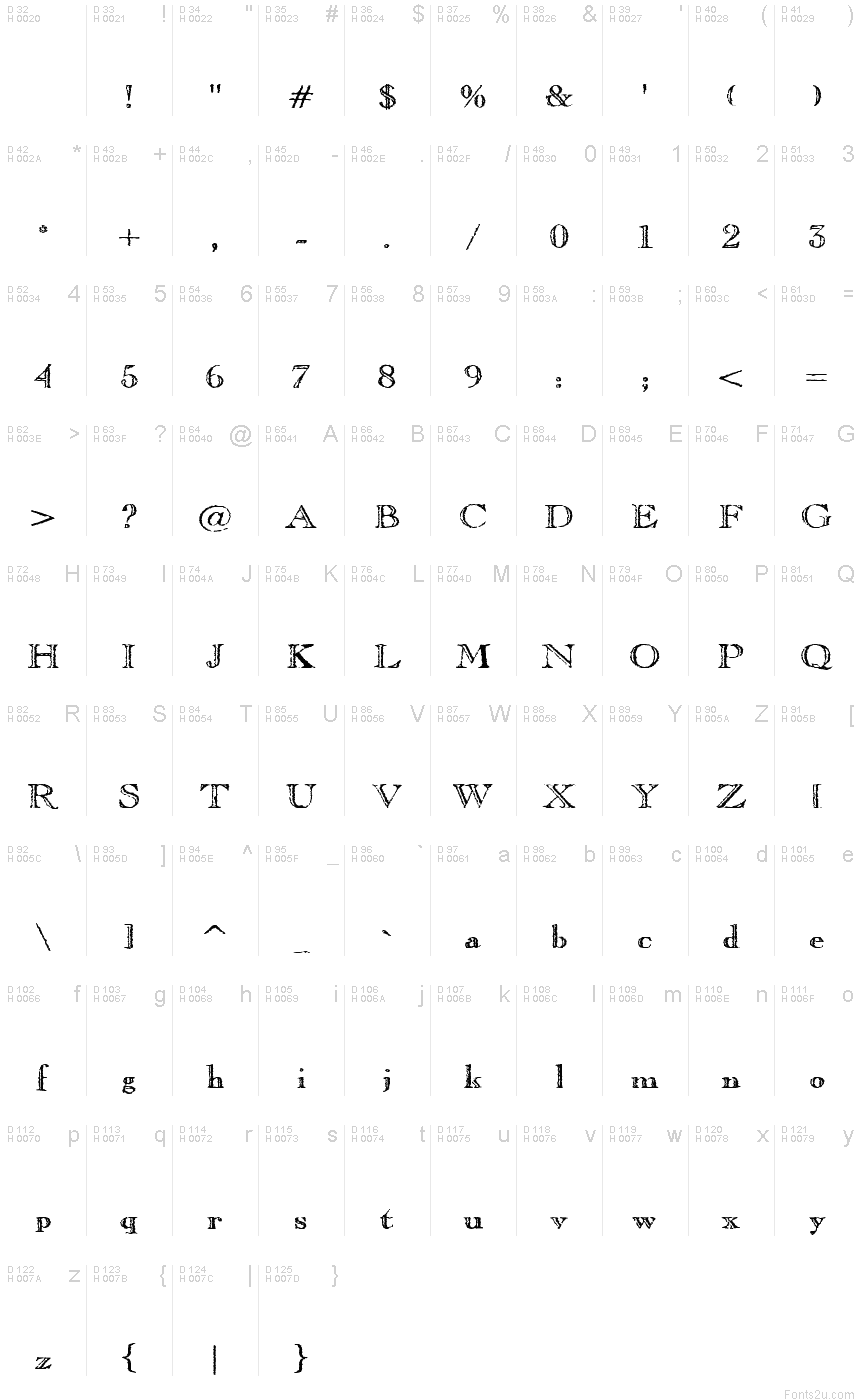
Old Copperfield od GemFonts98 to darmowy font typu display o erozyjnym charakterze, z szorstkimi, wyszczerbionymi krawędziami i przełamanymi konturami, które nadają każdej literze wygląd zwietrzałego, wycinanego napisu. Litery są wysokie i nierówne, z ostrymi cięciami i zadrapaniami, które zachowują efekt zużycia, nie tracąc przy tym swojej wyrazistej, dekoracyjnej formy.
Old Copperfield świetnie sprawdza się na plakatach horrorów, ulotkach wydarzeń o mrocznym klimacie, w tytułach gier, logotypach z efektem postarzenia oraz opakowaniach w stylu vintage, ponieważ poszarpane kontury błyskawicznie nadają projektom charakteru „z epoki”. Ten darmowy font doskonale pasuje również do okładek płyt, książek i wyrazistych nagłówków, gdzie spękany, staroświecki wygląd liczy się bardziej niż dopracowane wykończenie.